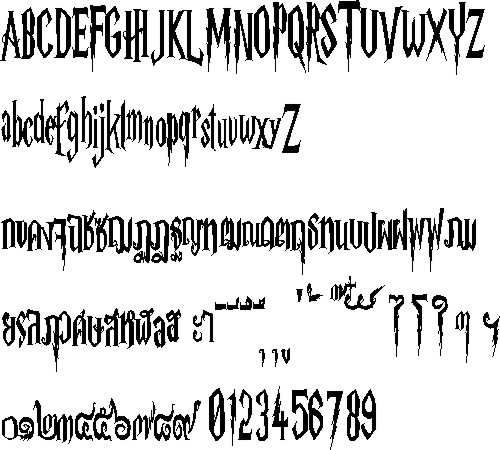
fontแรกในชีวิต
หน้าตามันให้มากเลยล่ะ ไม่เหมือนฟอนต์หลายๆตัวที่จะทำเลียนแบบ แต่ไปเหมือนเอาแต่ตัวที่มีแบบ
สงสัยอยู่อย่าง แล้วจะพิมพ์คำว่าจุดยังไงล่ะฮึ
ก็ทำเหมือนพิมพ์คำว่า "กตัญญู" สิบุ๊ค
สงสัยว่ามันเป็นตัวเดียวกับที่เห็นในตัวอย่างหนังเรื่องนีหรือเปล่าครับ
ถ้าทำออกมาได้เนี้ยบขนาดนี้นี่ไม่ใช่เล่นๆ แล้วนะ  :40:
เคยเห็นฟอนต์เรื่องแฮรี่พอตเตอร์มาแล้วล่ะ แต่เห็นเป็นตัวแบบอังกฤษอย่างเดียว
แต่ถ้าทำเป็นภาษาไทยแล้วก็
ขอบคุณพี่ Book ที่ช่วยชี้จุดบอด ตอนนี้แก้แล้ว พี่ๆช่วยพิจารณาอีกทีนะ นะ